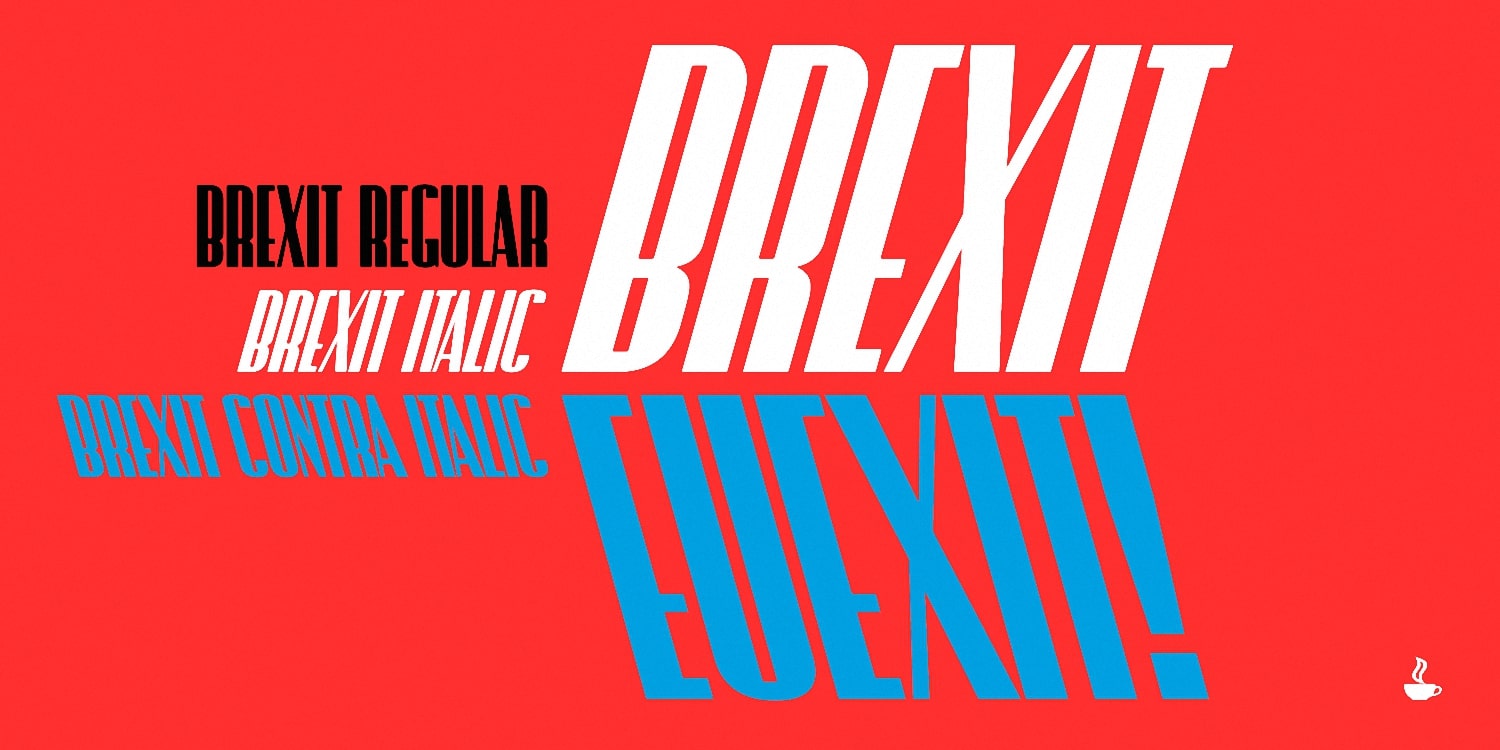
Шрифт Brexit
Это дерзкий акцидентный шрифт, созданный Сергеем Филиным (Sergey Filin). Он выполнен в стиле грубого трафарета и имитирует эффект аэрозольной краски или старого штампа. Кириллическая версия полностью поддерживает русский язык, сохраняя агрессивную эстетику оригинала. Шрифт обладает брутальным характером: его буквы имеют характерные «прорези» и неровные края, что придает ему вайб панк-культуры 70-х годов и протестного искусства. Он отлично подходит для задач, требующих мгновенного привлечения внимания: от афиш концертов до уличной графики. Вы можете скачать кириллицу бесплатно по ссылке ниже